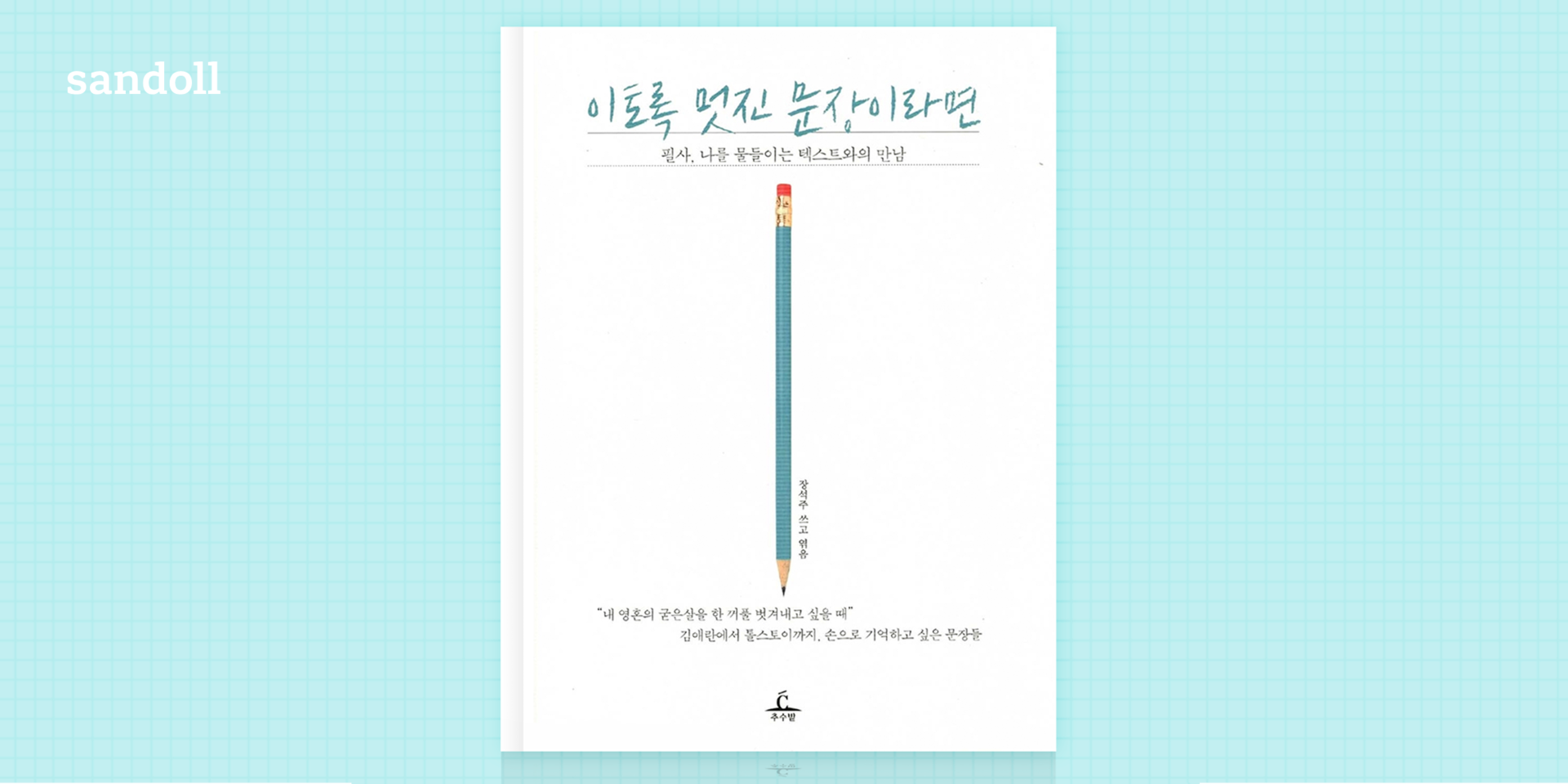
Sandoll 공병각필
산돌 공병각필은 색연필의 거친 질감이 공병각 작가의 손글씨로 고스란히 드러난 폰트이다.손글씨의 독특한 느낌을 살리기 위해 인위적인 보정이나 설정은 최대한 배제하였고 색연필로 적은 공병각 작가의 손글씨 원본 도안을 가능한 그대로 살려 표현하였다.